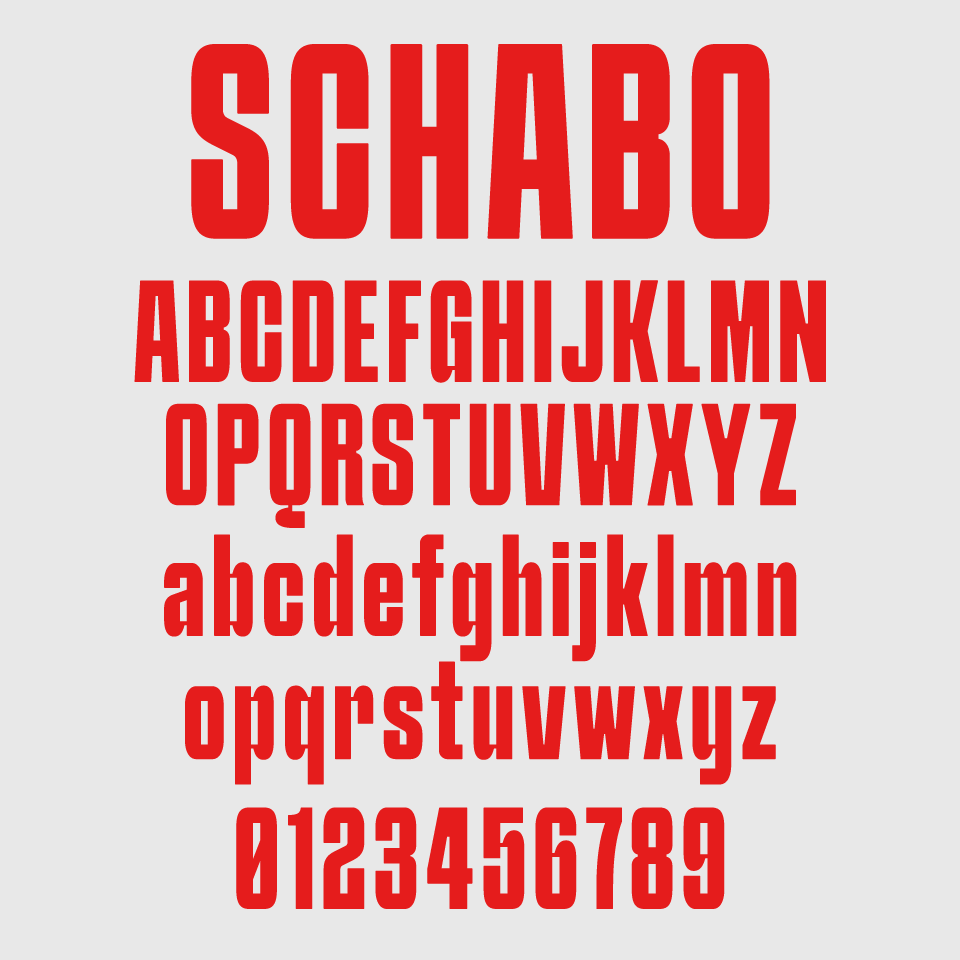
SCHABO CONDENSEDフォントは、無骨さと大胆さな縦長でコンデンスされたシルエットが印象的なサンセリフ体です。
上下にぎゅーっと引き伸ばされた形状が、存在感を一気に高めてくれます。太めの字幅と直線的なストロークが、インパクトを生む要素となっています。
さまざまな分野で活躍できるフォントですが、とくにスポーツ関連のタイポグラフィに取り入れると、力感と緊張感にぴったりです。
さらに縦に伸びた「SCHABO X CONDENSED」というフォントもあります。